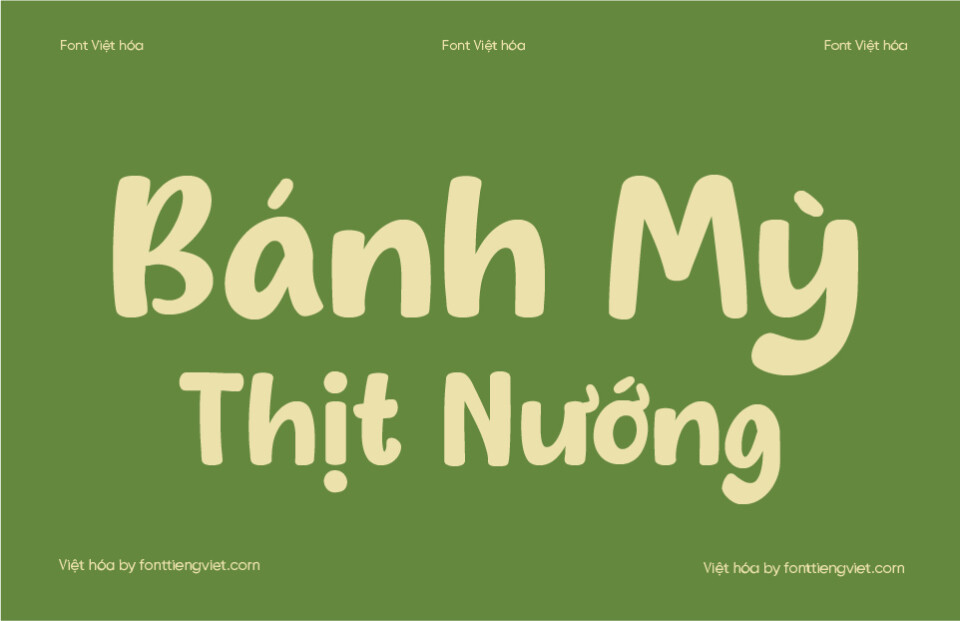
Font Việt hóa TF Mayura – Font ngộ nghĩnh dễ thương Việt Hóa
Font Việt hóa TF Mayura – Font ngộ nghĩnh dễ thương
Tên font: Font Việt hóa TF Mayura – Font ngộ nghĩnh dễ thương
Tác giả: FontVietHoa.Org
Font Việt hóa TF Mayura có nét béo tròn, font phù hợp với thiết kế ẩm thực hoặc thiết kế liên quan tới trẻ em.